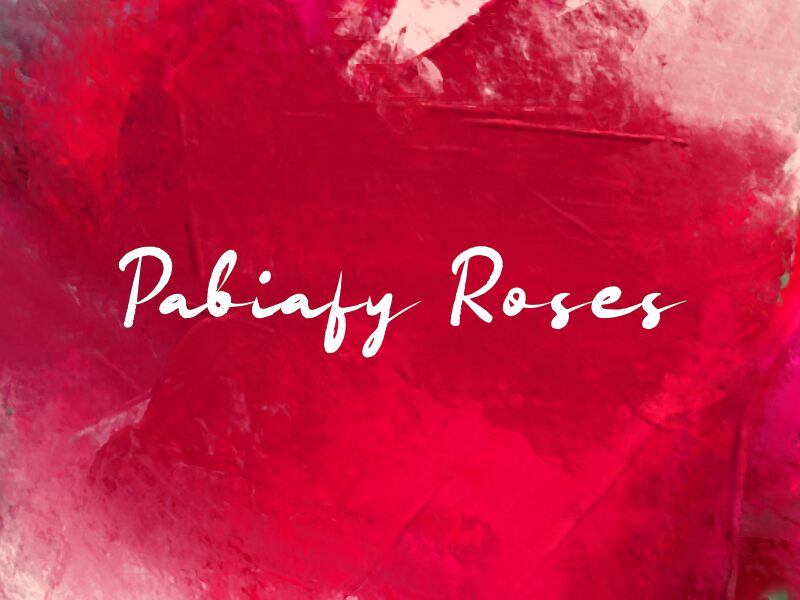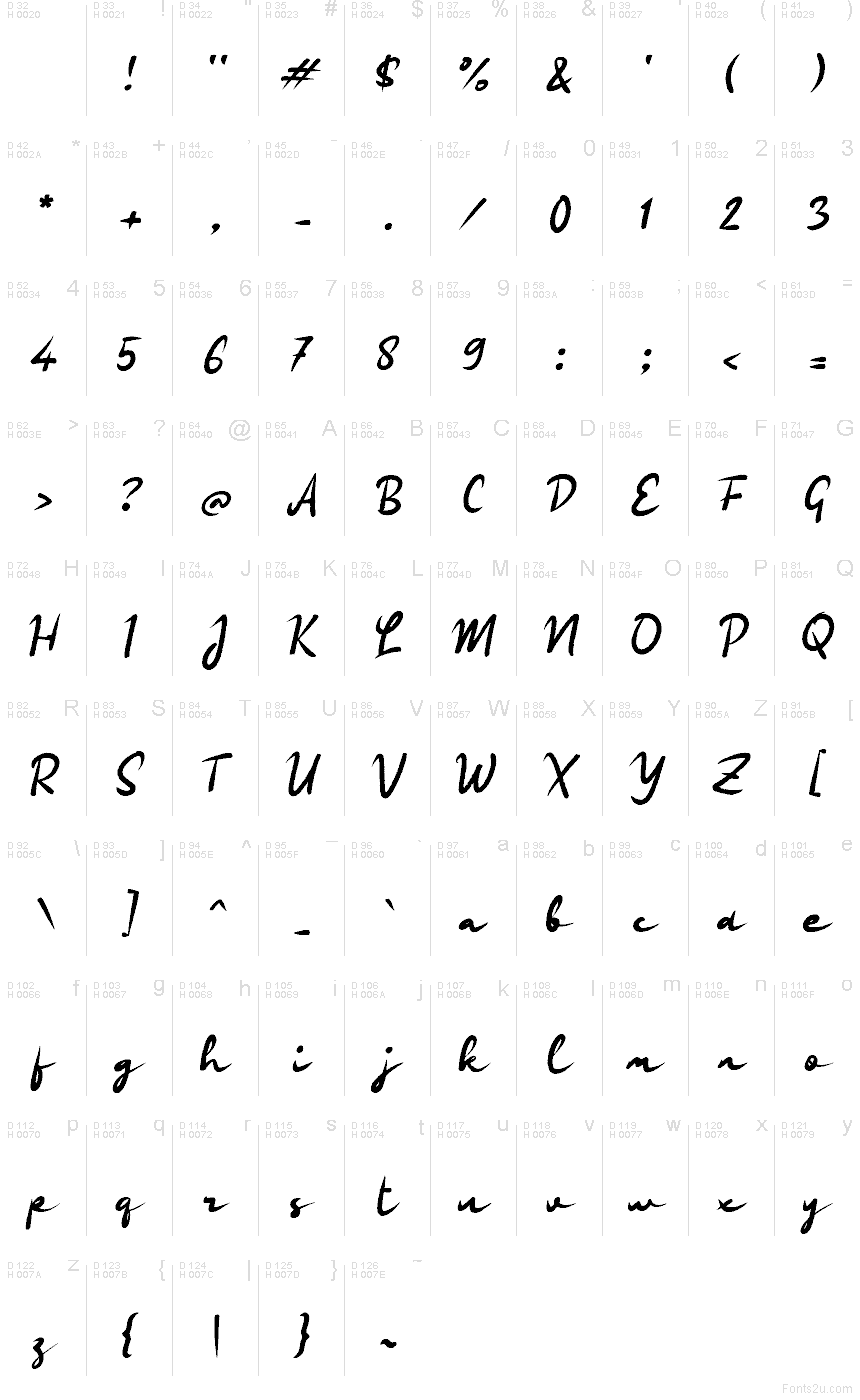
Pabiafy Roses
Pabiafy Roses od Ikiik je bezplatné ručně psané písmo typu script, utvářené rychlými tahy štětcem a volným, plynulým rytmem. Písmo střídá široké malované tahy s jemnými spojnicemi, což mu dodává ležérní nádech psaní fixou namísto uhlazené kaligrafické sady.
Díky tomu je přirozenou volbou pro loga butiků, obaly produktů, jídelní lístky kaváren, svatební tiskoviny nebo záhlaví sociálních sítí, kde záleží na osobním podpisu. Zametavé začátky písmen a zaoblená malovaná textura navíc pomáhají krátkým větám působit živě na dárkových visačkách, etiketách svíček nebo v beauty brandingu, aniž by působily příliš formálně.